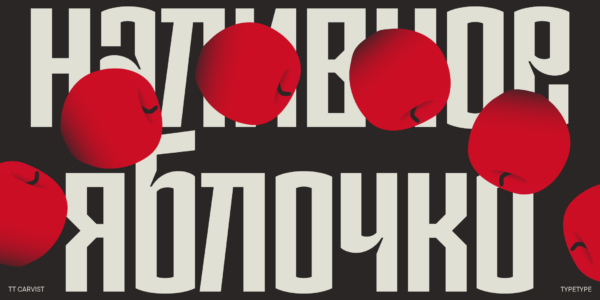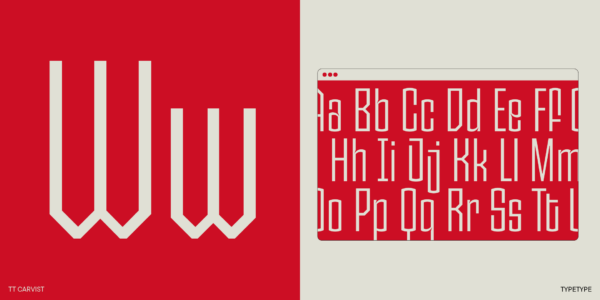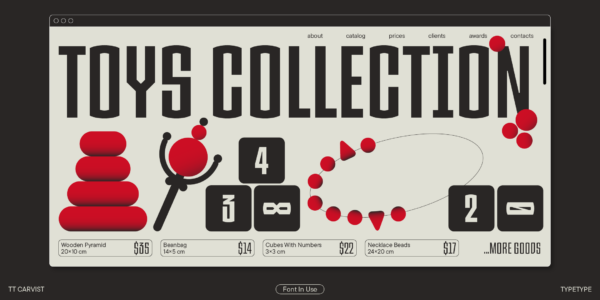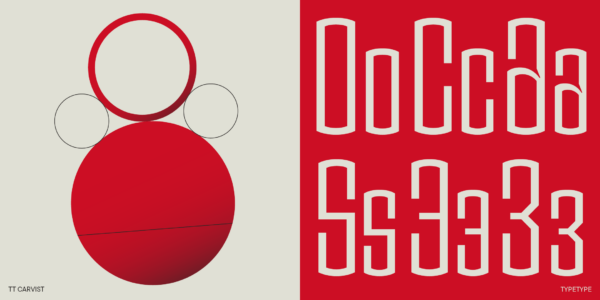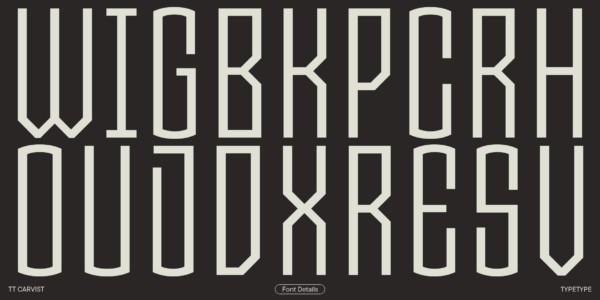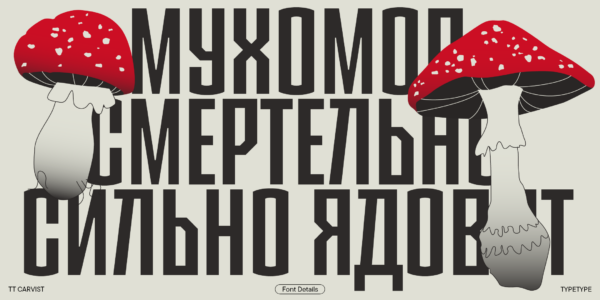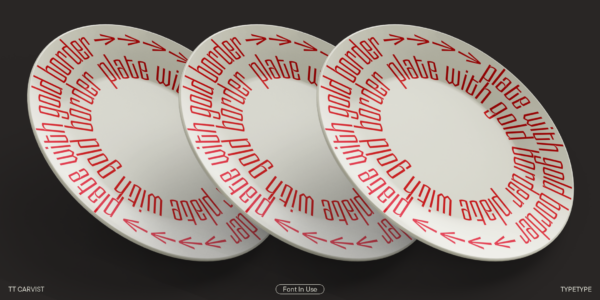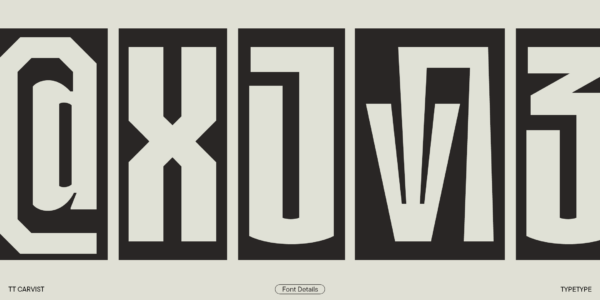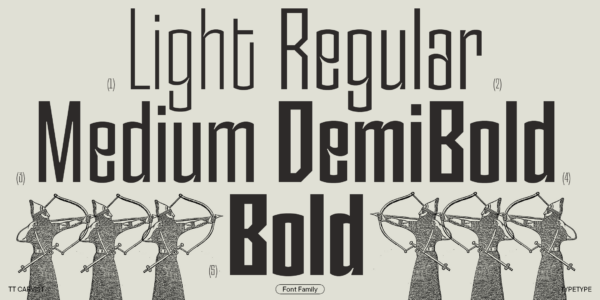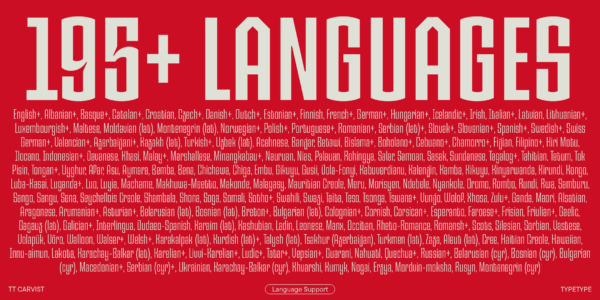
TT Carvist — ТТ Карвист
Произносится «ТТ Карвист». «Carvist» — производное слово от carving, в переводе с английского «вырезание». Буквы «TT» являются аббревиатурой названия компании.
TT Carvist — экспериментальный гротеск со сверхузкими пропорциями. Это самобытный акцидентный шрифт с готическим настроением.
Современный геометрический гротеск с узкими пропорциями
В 2021 году мы поняли, что наш модульный гротеск TT Tunnels морально устарел, и решили визуально освежить его. Так начался поиск новых визуальных решений, которые могли бы лечь в основу обновленной гарнитуры. Он продолжался в течение нескольких месяцев — и, наконец, мы нашли подходящий визуальный стиль. Обновленное шрифтовое семейство получило название TT Carvist. В основу латиницы мы заложили легкое послевкусие готического письма, а кириллическую часть внедрили нотки из вязи. Так, шрифт получился самобытным, озорным и местами дерзким. Несмотря на то, что новое шрифтовое семейство является модульным, мы качественно проработали каждый контур, все скругления и завитки.
Семейство состоит из 6 начертаний: 5 прямых и 1 вариативного
TT Carvist одинаково хорошо подойдет для театральных афиш и для анонсов мероприятий
TT Carvist в дизайне
О гарнитуре TT Carvist
Поддержка языков 200+
Встречайте TT Carvist — новый акцидентный шрифт от TypeType! Самобытный, озорной и дерзкий — он умеет привлекать внимание!
TT Carvist — современный экспериментальный гротеск со сверхузкими пропорциями. За основу для его создания мы взяли шрифт TT Tunnels, однако в процессе работы проект вырос в нечто абсолютно новое и уникальное.
TT Carvist отличается модульностью, диагональными 45-градусными внешними срезами, закрытыми апертурами и характерными крупными компенсаторами в строчных буквах. Интересно, что в нем совсем нет круглых знаков: например, «О» и «С» скруглены сверху и снизу, но прямые по бокам. Это решение можно увидеть и в треугольных знаках («v», «w», «y») — стемы у них прямые.
Название гарнитуры отсылает к резьбе по камню: характерные черты этого шрифта — геометричность и брутальность. При этом TT Carvist умеет быть разным. Так, в начертании bold он выглядит довольно массивно и напоминает непроходимый лабиринт, почти не оставляя пространства между знаками. В начертании light, напротив, появляется легкость и изящность, его рисунок напоминает невесомое кружево.
Кроме того, мы добавили в шрифт альтернативные знаки и символы, которые позволяют стилизовать его для разных задач и делать еще более причудливым. В частности, «плетеные» цифры 3 и 8, прописные «A» и «Y», повторяющие рисунок строчных, характерная прописная «Е» и трехногая кириллическая «т», необычные оборотные стрелочки и нестандартная «@».
В латинице TT Carvist приобретает готическое настроение, а в кириллице становится похожим на вязь. При этом шрифт выглядит свежо и актуально, что позволяет использовать его для оформления книг и журналов, плакатов и афиш, анонсов мероприятий и многого другого.
TT Carvist — это:
• 6 начертаний: 5 прямых и 1 вариативный шрифт, способный меняться по оси жирности;
• 803 глифа в каждом начертании;
• 29 OpenType фич, в том числе возможность менять некоторые знаки на альтернативные, а также дополнительные символы;
• Поддержка более 195 языков.
Если в вашей коллекции не хватает своеобразного и стильного акцидентного шрифта, TT Carvist станет ее ярким дополнением!
Антонина Жулькова
Алина Габидулова
Юрий Наконечный
ss01 | Latin and Cyrillic A
ss02 | Latin and Cyrillic E
ss04 | Latin and Cyrillic a
ss05 | Double-storey Latin g
ss07 | Alternative 3 and 8
case | Case Sesitive